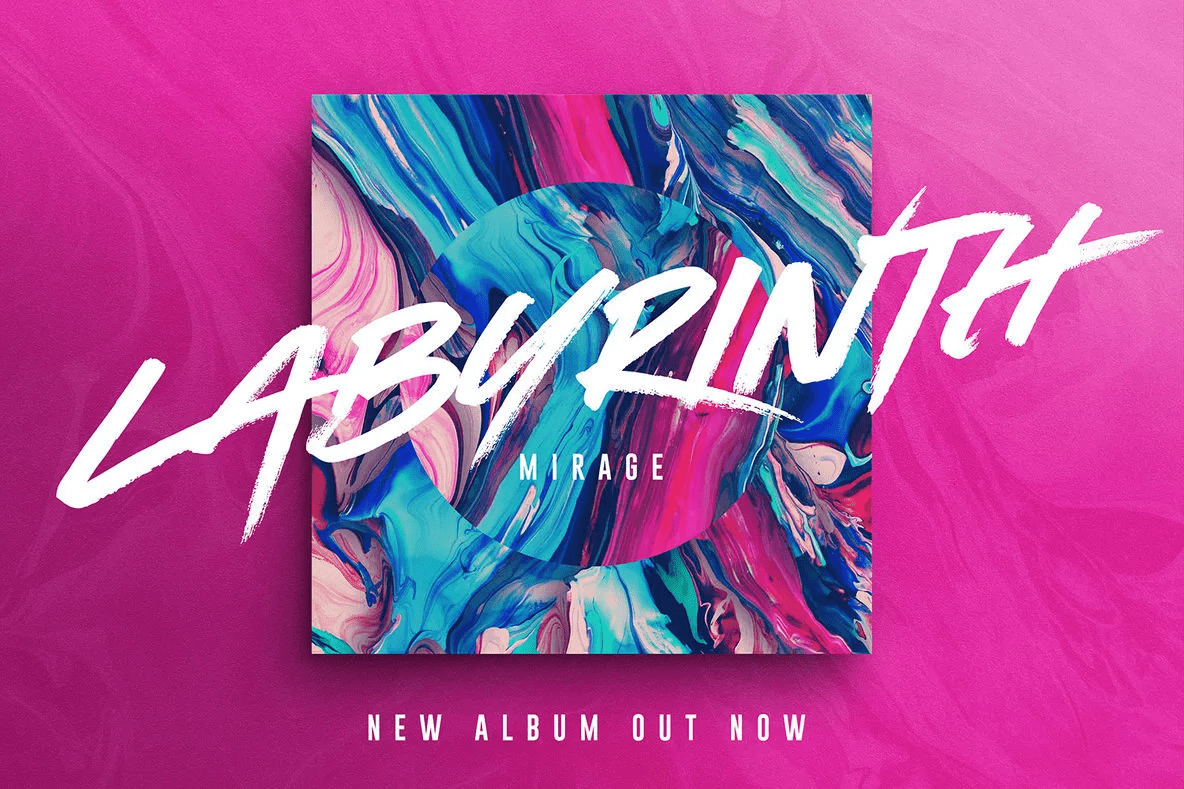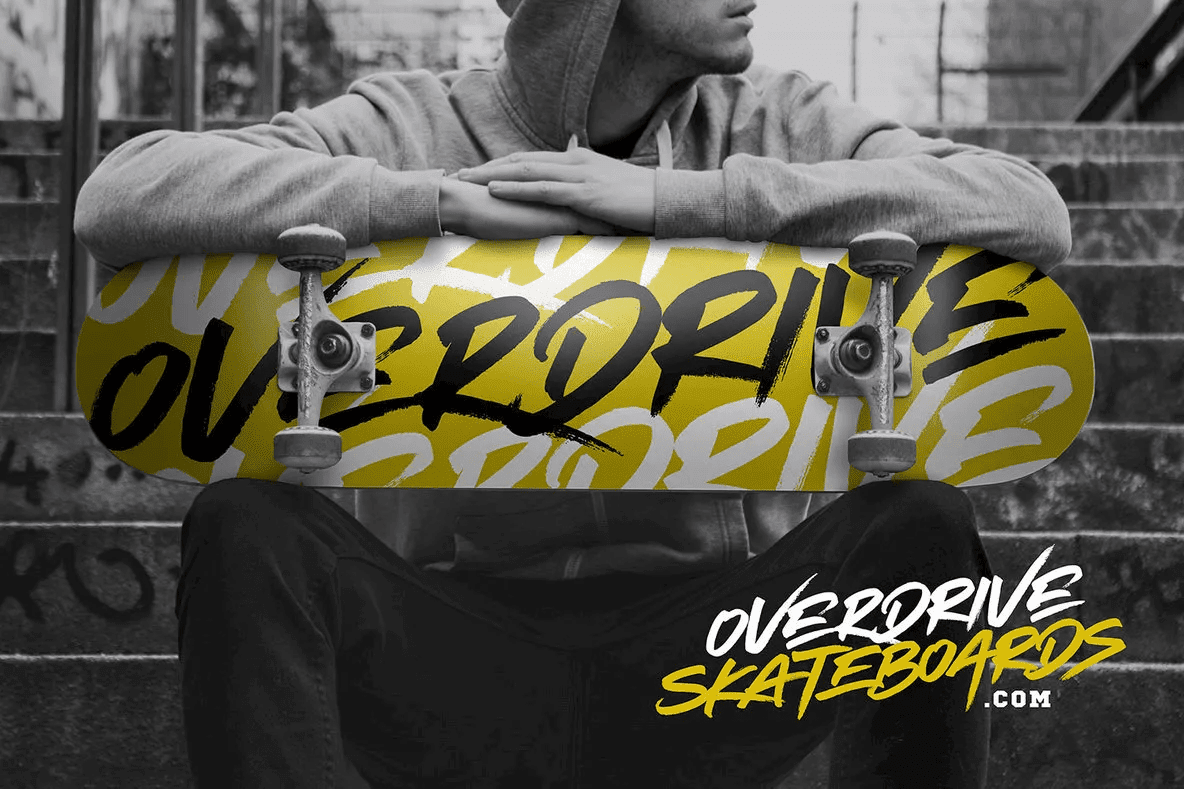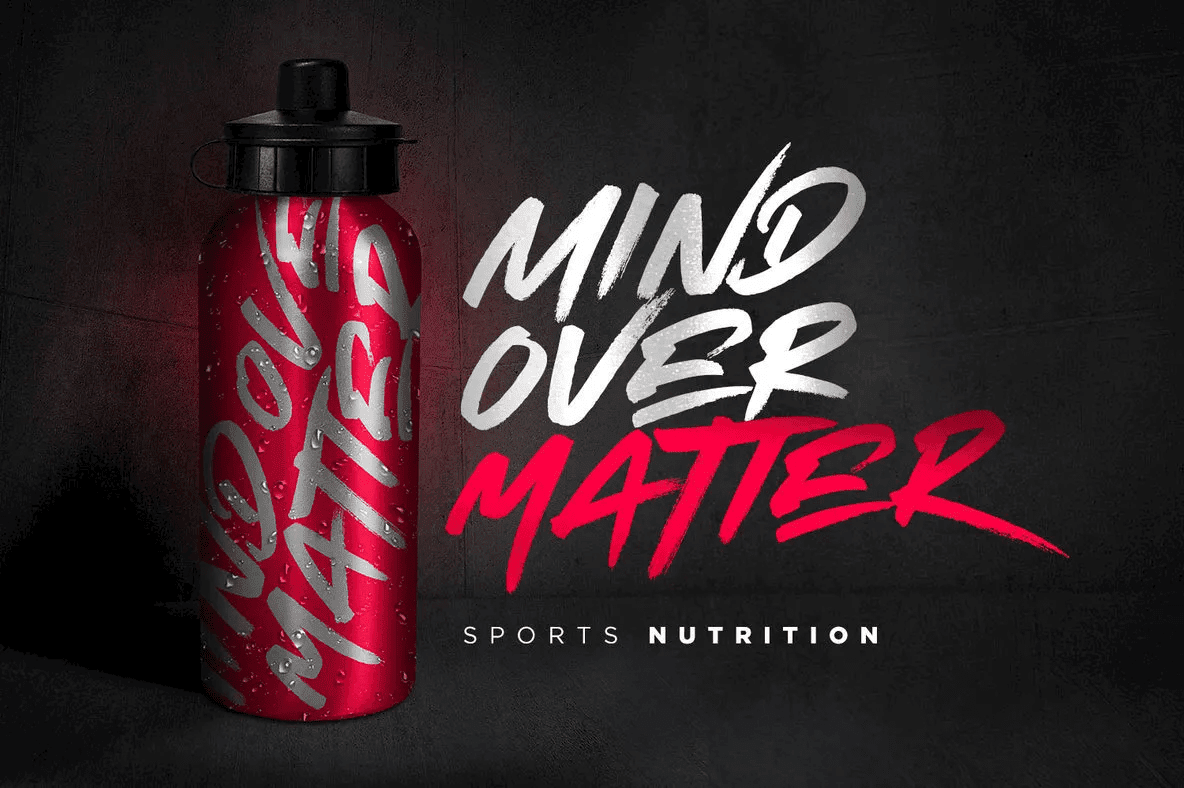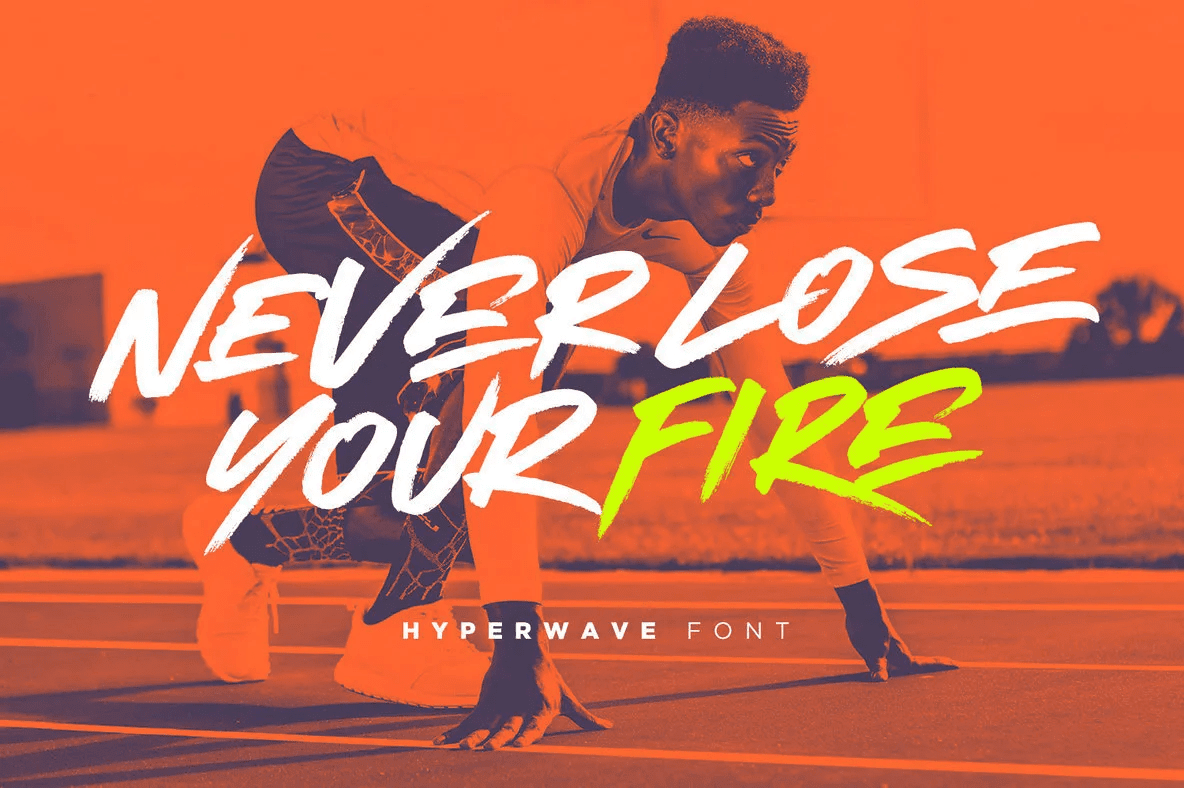
Tăng cường độ với HYPERWAVE! Một bộ phông chữ cọ tràn đầy năng lượng với thái độ sắc nét.
Với BA bộ mỗi chữ cái, mỗi bộ được trang bị những nét vẽ nhanh đặc biệt, HYPERWAVE sẵn sàng và hiếm hoi để đưa ra tuyên bố lớn về thiết kế logo, hình ảnh thương hiệu, trích dẫn viết tay, bao bì sản phẩm, hàng hóa, dự án âm nhạc và bài đăng trên mạng xã hội của bạn.
HYPERWAVE có 3 kiểu phông chữ:
1. Hyperwave One • Phông chữ bút đánh dấu thủ công chỉ chứa các ký tự viết hoa, chữ số và một loạt dấu câu lớn.
2. Hyperwave Two • Đây là phiên bản thứ hai của Hyperwave, với bộ ký tự viết hoa hoàn toàn mới. Nếu bạn muốn tránh các chữ cái trông giống nhau mỗi lần tạo lại kiểu tùy chỉnh hoặc thử hình dạng từ khác, chỉ cần chuyển sang phông chữ này để có tùy chọn bố cục bổ sung.
3. Hyperwave Ba • Bạn đoán rồi; phiên bản thứ ba của Hyperwave, với một bộ ký tự viết hoa hoàn toàn mới khác – mang đến cho bạn THÊM tùy chọn bố cục cho văn bản của bạn.